24개의 최고의 문신 글꼴 ️ 2023(무료 및 유료)
게시 됨: 2023-05-02프로젝트를 향상시키기 위해 독특하고 눈길을 끄는 글꼴을 찾고 있는 그래픽 디자이너입니까? 24개의 최고의 문신 글꼴 목록을 살펴보세요.
이 기사에서는 디자인에 세련미와 창의성을 더할 수 있는 다양한 글꼴을 살펴봅니다. 4,500만 명 이상의 미국인이 적어도 하나의 문신을 하고 있는 가운데 문신이 최근 몇 년 동안 더욱 주류가 된 자기 표현 및 예술의 한 형태임이 분명합니다.
이 기사에서는 다음 프로젝트에 영감을 줄 가장 인기 있는 문신 글꼴 중 일부를 강조합니다.
이 기사에서는 각각 고유한 스타일과 감각이 있는 24개의 최고의 타투 글꼴을 소개합니다. 문신을 디자인하든 작업에 문신 스타일의 글꼴을 통합하든 이 포괄적인 가이드에서 많은 영감을 얻을 수 있습니다.
편안히 앉아 긴장을 풀고 문신 글꼴의 세계로 여행을 떠나십시오.
최고의 프리미엄 문신 글꼴
당신은 당신의 디자인에 날카로운 감각을 더하고 싶은 그래픽 디자이너입니까? 문신 글꼴을 작업에 통합하는 것을 고려했지만 어디서부터 시작해야 할지 몰랐습니까? 최고의 프리미엄 문신 글꼴 목록을 제공하므로 더 이상 보지 마십시오.
아메리칸 트래디셔널
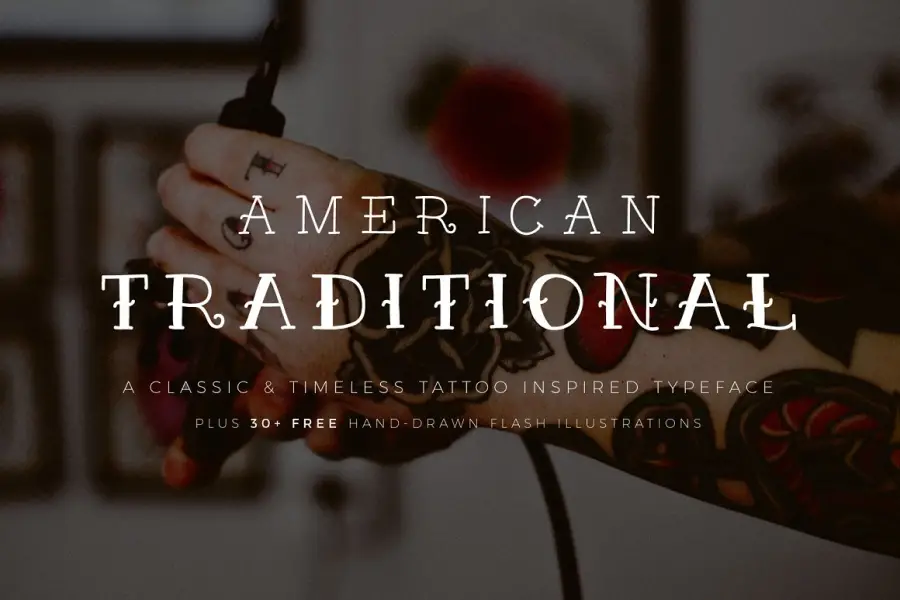
American Traditional은 미국의 전통적인 문신에서 영감을 받아 두 가지 두께로 제공되는 손글씨 글꼴입니다. 이 서체는 대담하고 눈길을 끄는 글자를 만들어 내므로 진정성 있고 빈티지한 느낌이 필요한 디자인에 적합합니다.
아메리칸 트래디셔널 폰트는 굵은 선과 둥근 모서리로 디자인되어 클래식한 타투 룩을 연출할 수 있으며 타투 관련 비즈니스 웹사이트에서도 사용할 수 있습니다. 여기에는 두 가지 가중치가 있어 디자이너가 프로젝트의 필요에 따라 더 섬세하거나 더 대담한 글꼴 중에서 선택할 수 있습니다. 이 글꼴은 포스터, 전단지, 로고 및 고전적이고 구식 분위기가 필요한 기타 디자인을 만드는 데 이상적입니다.
역사적인
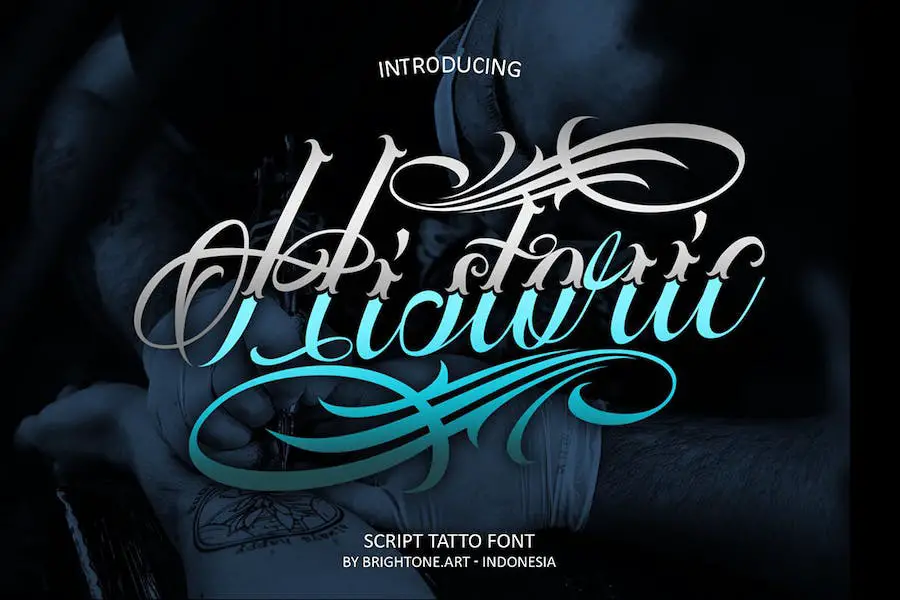
Historic은 대문자, 숫자, 다양한 구두점 및 다국어 지원과 함께 제공되는 스크립트 문신 스타일의 글꼴입니다. 이 전문 스크립트 글꼴은 로고 레터링, 셔츠 디자인, 로고 문신 스튜디오, 문신 디자인, 잡지, 브랜딩 등에 고유한 스타일을 제공합니다.
Historic을 사용하면 시선을 사로잡는 로고, 포스터, 전단지, 초대장 등을 만들 수 있습니다. 글꼴에 포함된 숫자, 구두점 및 다국어 지원은 호환성 문제나 언어 장벽에 대한 걱정 없이 모든 프로젝트에 글꼴을 쉽게 통합할 수 있음을 의미합니다.
전반적으로 전문적이고 다재다능한 스크립트 문신 스타일 글꼴을 찾고 있다면 Historic이 탁월한 선택입니다. 독특한 스타일과 다양한 기능으로 작업을 향상시키려는 디자이너에게 필수품입니다.
와일드스타일
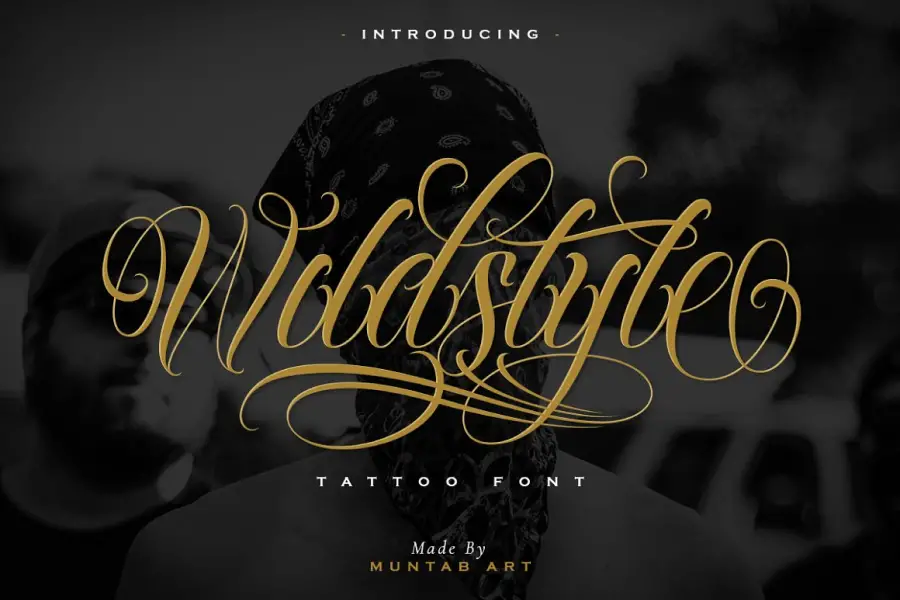
Wildstyle은 디자인 프로젝트에 감각과 개성을 더하고 싶은 모든 사람에게 완벽한 새로운 글꼴입니다. 이 Chicano Tattoo Style 글꼴에는 대문자와 소문자뿐만 아니라 숫자와 다양한 문장 부호가 포함됩니다. 고유한 스타일과 다양한 기능을 갖춘 Wildstyle은 문신 숫자 글꼴에 적합합니다.
Wildstyle의 눈에 띄는 기능 중 하나는 대문자와 소문자를 모두 포함하여 디자인에서 더 넓은 범위의 사용자 정의가 가능하다는 것입니다. 또한 글꼴에는 다양한 대체 문자와 소문자에 대한 종료 스와시가 포함되어 디자인을 돋보이게 합니다.
문신 야수
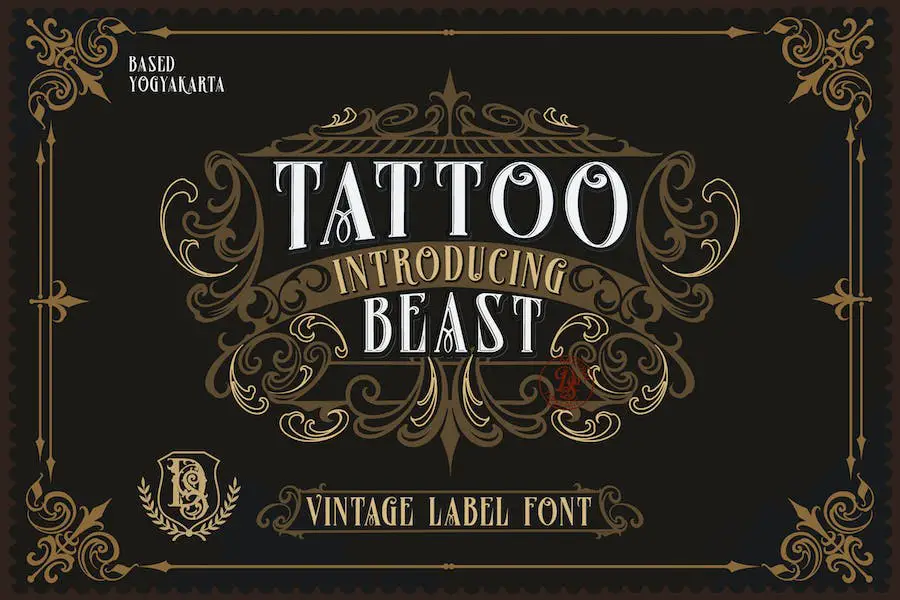
Tattoo Beast는 자신의 디자인에 빈티지한 감각을 더하고 싶은 모든 사람에게 꼭 필요한 글꼴입니다. 이 블랙레터 글꼴은 우아하고 매우 섬세하여 로고, 포스터, 헤드라인 등에 사용하기에 적합합니다.
Tattoo Beast의 눈에 띄는 특징 중 하나는 다재다능함입니다. 제품 로고, 배지 또는 의류 브랜드 로고를 디자인하든 이 글꼴은 창작물을 다음 단계로 끌어올릴 수 있는 잠재력을 가지고 있습니다. 또한 빈티지 디자인을 위한 훌륭한 선택으로 작품에 진정성을 더해줍니다.
Tattoo Beast를 차별화하는 또 다른 점은 독특한 모양입니다. 글자의 복잡한 세부 사항은 독특하고 눈길을 끄는 모양을 제공하여 귀하의 디자인을 군중들로부터 돋보이게 합니다.
배사이드
BaeSide는 다양한 대체 글꼴, 합자 및 화려한 요소와 함께 제공되는 우아한 Blackletter 디스플레이 글꼴입니다. 이 현대적인 글꼴은 독특하고 화려한 감각이 필요한 문신 가게, 음료 라벨, 의류 라벨 및 기타 응용 프로그램에서 사용하도록 특별히 설계되었습니다. 또한 클래식 문신 글꼴에 적합합니다.
BaeSide 글꼴은 기본 라틴 숫자와 구두점 문자를 모두 포함하지만 다국어가 아니라는 점에 유의해야 합니다. 이러한 제한에도 불구하고 BaeSide는 특히 많은 대체 서체 및 장식 요소와 함께 사용할 때 여전히 다양한 기능과 창의적인 잠재력을 제공합니다.
가명
Incognito의 눈에 띄는 기능 중 하나는 클래식한 모양으로, 초초하거나 빈티지한 느낌의 디자인을 만드는 데 적합합니다. 글꼴의 굵은 선과 날카로운 각도는 눈에 띄어야 하는 헤드라인이나 제목에 적합합니다. 또한 고유한 스타일로 미스터리한 느낌을 주기 때문에 약간의 호기심이 필요한 프로젝트에 적합합니다.
문신을 한 까마귀
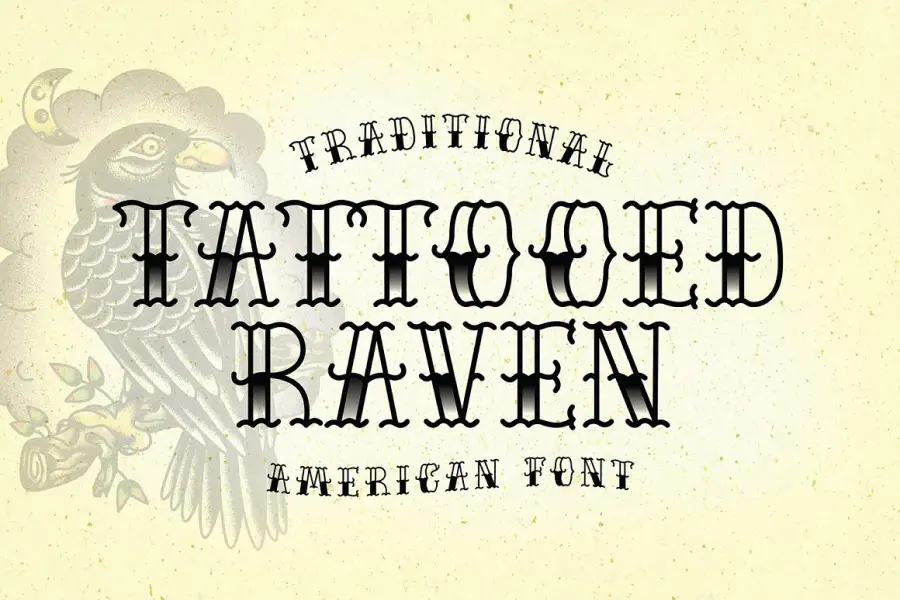
Tattooed Raven은 디자인 프로젝트에 약간의 엣지를 더할 글꼴입니다. 아메리칸 트래디셔널 타투 스타일은 대담한 헤드라인과 일러스트레이션에 적합하며 특히 로고와 의류 디자인에 적합합니다.
Tattooed Raven을 사용할 때는 모두 대문자를 사용하는 것이 좋지만 소문자는 재미있는 장식 요소와 함께 제공되어 프로젝트에 개성을 더할 수 있습니다. 보너스로 그라데이션 효과가 포함된 글꼴 버전도 있습니다.
킹사이드
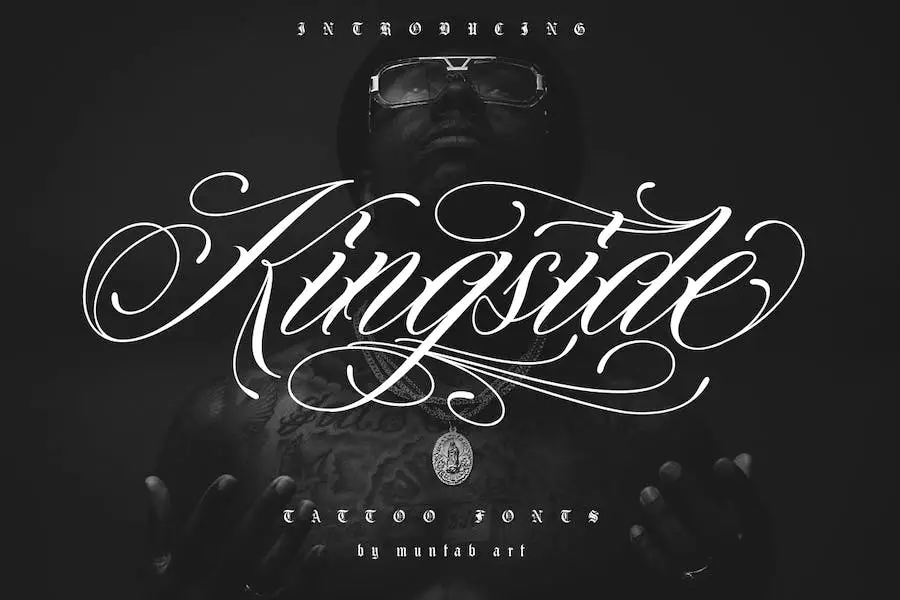
Kingside는 문신 스타일 디자인을 위해 특별히 제작된 새로운 글꼴입니다. 고유한 기능을 갖춘 Kingside는 프로젝트 디자인을 개선하려는 그래픽 디자이너에게 다양한 가능성을 제공합니다. 또한 디자인에 타투 레터링 글꼴을 사용할 수 있습니다.
이 글꼴에는 대문자와 소문자, 숫자, 다양한 구두점 및 합자가 포함됩니다. Kingside의 가장 주목할만한 기능 중 하나는 모든 소문자에 엔딩 스와시와 대체 글꼴이 포함되어 있다는 것입니다. 이것은 글꼴로 디자인할 때 더 큰 창의성과 개인화를 허용합니다.
Kingside에서 사용할 수 있는 대체 글꼴 옵션은 디자이너에게 다양한 기능을 제공합니다. 보다 전통적인 느낌을 원하든 현대적인 느낌을 원하든 Kingside가 도와드립니다.
크래시번
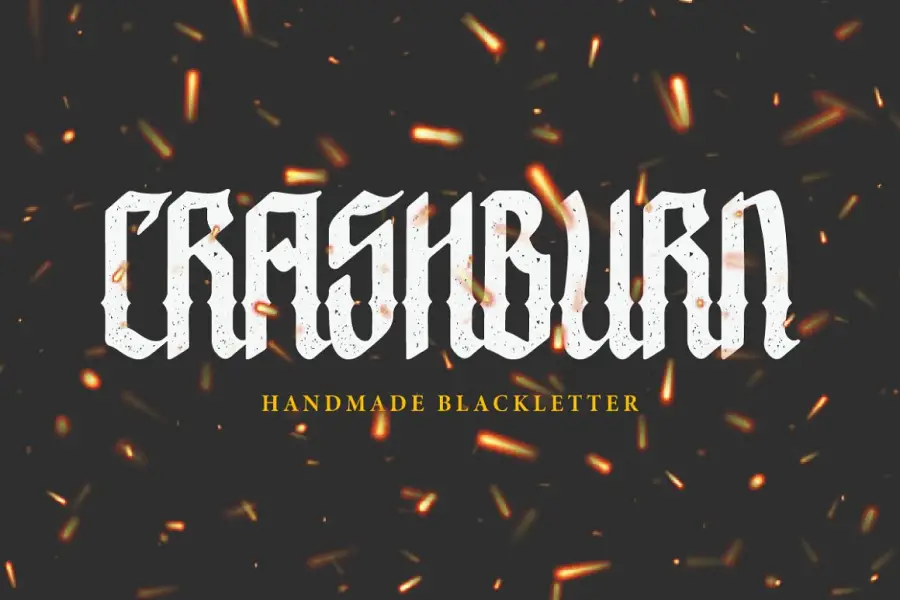
Crashburn은 Clean, Textured, Inline 및 Outline의 네 가지 고유한 스타일로 제공되는 강력한 새 글꼴입니다. 이 Blackletter 글꼴은 상품 디자인, 스트리트웨어, 티셔츠 디자인, 로고, 타이포그래피 디자인, 포스터, 패키징, 브랜딩 또는 멋진 느낌을 추가해야 하는 모든 것에 독특한 터치를 추가하려는 모든 사람에게 적합합니다.
Crashburn의 클린 스타일은 세련되고 현대적이며 미니멀한 룩을 찾는 모든 사람에게 적합합니다. 반면 Textured 스타일은 날카롭고 거친 느낌이 있어 도시적인 디자인과 잘 어울립니다. 인라인 스타일은 텍스트에 깊이와 치수를 추가하는 데 적합하며 아웃라인 스타일은 시선을 사로잡는 효과를 만들어냅니다.
럼블 타투
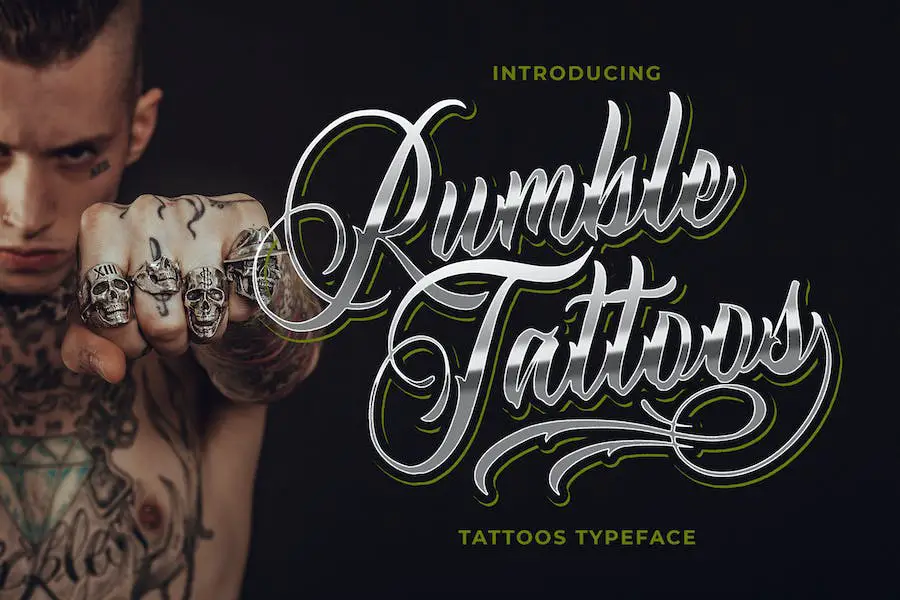
Rumble Tattoos 서체는 문신 애호가를 위해 특별히 설계된 새로운 스크립트 글꼴입니다. 이 서체는 로고타입 타투, 포스터 타투, 상품 타투를 만들기에 완벽한 독특한 스타일을 가지고 있습니다. 또한 Canva용 타투 글꼴을 사용할 수 있습니다.
Rumble Tattoos Typeface의 눈에 띄는 기능 중 하나는 다용도성입니다. 다양한 디자인 프로젝트에 사용할 수 있으므로 프로젝트 디자인을 개선할 수 있는 글꼴을 찾는 그래픽 디자이너에게 탁월한 선택입니다.
이 서체의 또 다른 큰 특징은 독특한 디자인입니다. 글자는 대담하고 곡선미가 있어 시선을 사로잡는 독특한 모양을 제공합니다. 또한 이 글꼴은 다양한 크기로 제공되므로 프로젝트에 적합한 크기를 선택할 수 있습니다.
객실
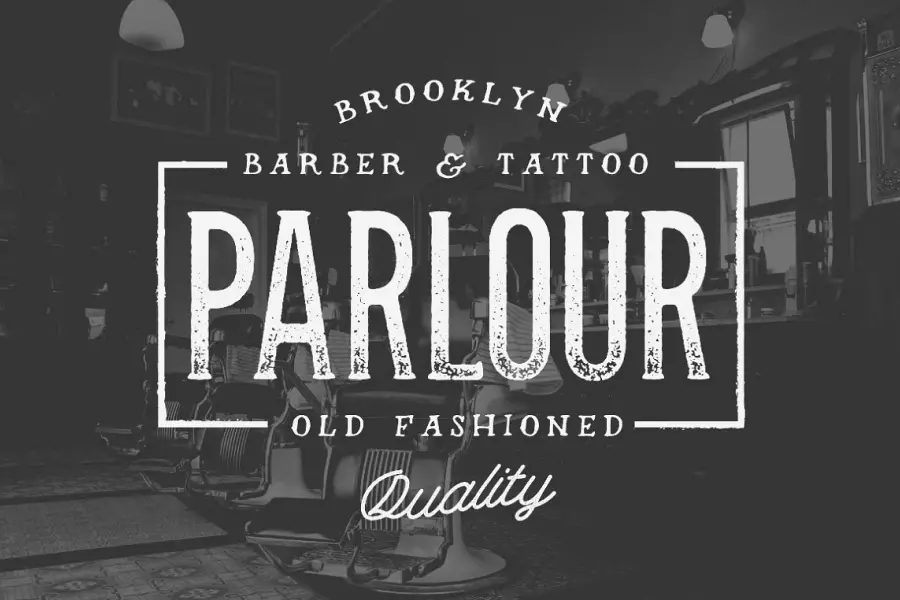
'Parlour'는 Movember, Menswear Brands, Tattoo Shops & Barbers에서 영감을 얻어 Hustle Supply Co.에서 디자인한 스타일리시한 디스플레이 서체입니다. 이 글꼴은 프로젝트에 독특하고 엣지 있는 터치를 추가하려는 디자이너에게 적합합니다. 또한 Figma의 문신 글꼴에 적합합니다.
이 글꼴은 매우 다재다능하며 디자인에 개성과 깊이를 더하는 사전 적용된 텍스처와 함께 제공됩니다. 글꼴은 OTF 형식으로 제공되며 전체 알파벳, 숫자, 구두점 및 추가 글리프를 포함합니다. 이 글꼴은 모든 문자가 잘 디자인되고 읽기 쉽도록 소프트웨어 Glyphs를 사용하여 생성되었습니다.
이 서체는 HSCo에서 출시한 두 번째 서체이며, 고품질 서체를 만드는 이러한 추세를 계속 이어갈 계획입니다. 사용자가 자신의 창작물을 공유하고 댓글 섹션에서 피드백을 제공하도록 권장합니다. 당신의 디자인을 돋보이게 할 폰트를 찾고 있다면 '팔러'는 확실히 고려해 볼 가치가 있습니다.
모건 문신
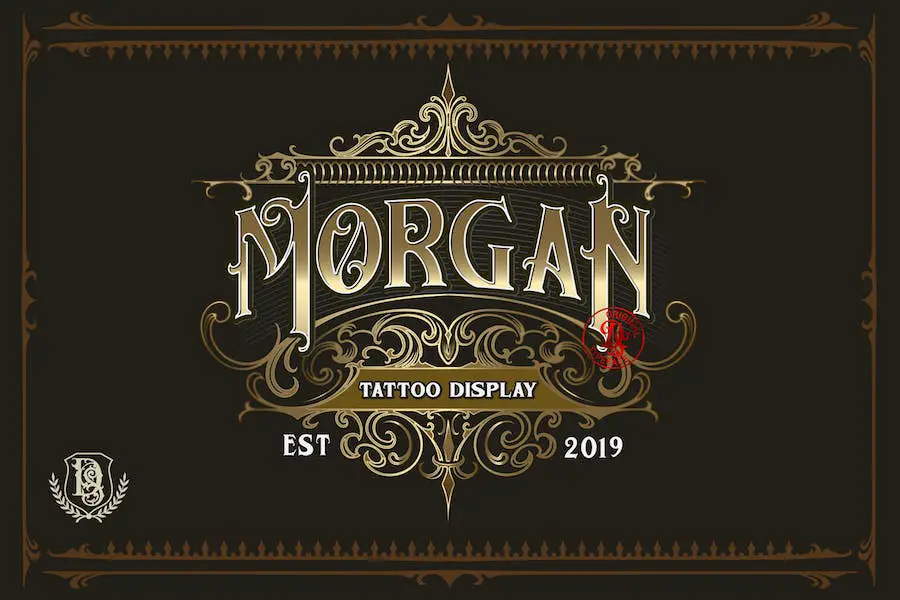
Morgan Tattoo는 모든 프로젝트의 디자인을 개선할 수 있는 멋진 블랙레터 문신 글꼴입니다. 이 글꼴은 다목적이며 제품 로고, 포스터 제목, 헤드라인, 의류 브랜드 로고, 빈티지 디자인 등과 같은 다양한 용도로 사용할 수 있습니다. 또한 독특한 모양의 Morgan Tattoo는 Google Tattoo Fonts의 모든 창작물을 향상시킬 수 있는 잠재력을 가지고 있습니다.
결론
결론적으로 그래픽 디자이너가 프로젝트 디자인을 향상시키는 데 사용할 수 있는 최고의 문신 글꼴 24개에 대해 논의했습니다. 전통적인 블랙레터 글꼴에서 현대적인 붓글씨 스크립트에 이르기까지 모든 디자인 스타일에 맞는 글꼴이 있습니다. 이 기사가 유익하고 도움이 되었기를 바랍니다.